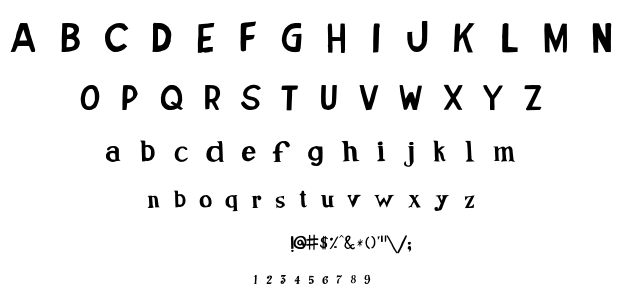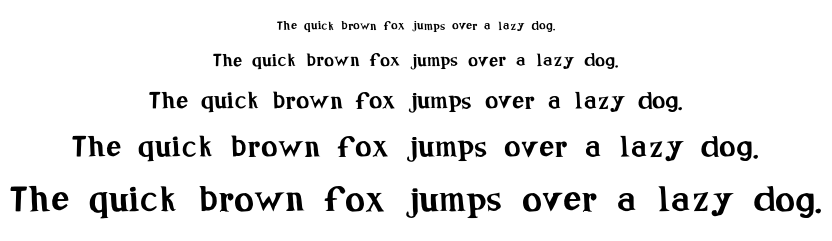
Essa fonte feita a mão por José de Oliveira, pintor profissional e cineasta amador nascido na cidade de São Carlos, interior do estado de São Paulo, Brasil.
Ela foi criada para o filme Delírios de um cinemaníaco e agora está disponível na internet para ser distribuída gratuitamente.